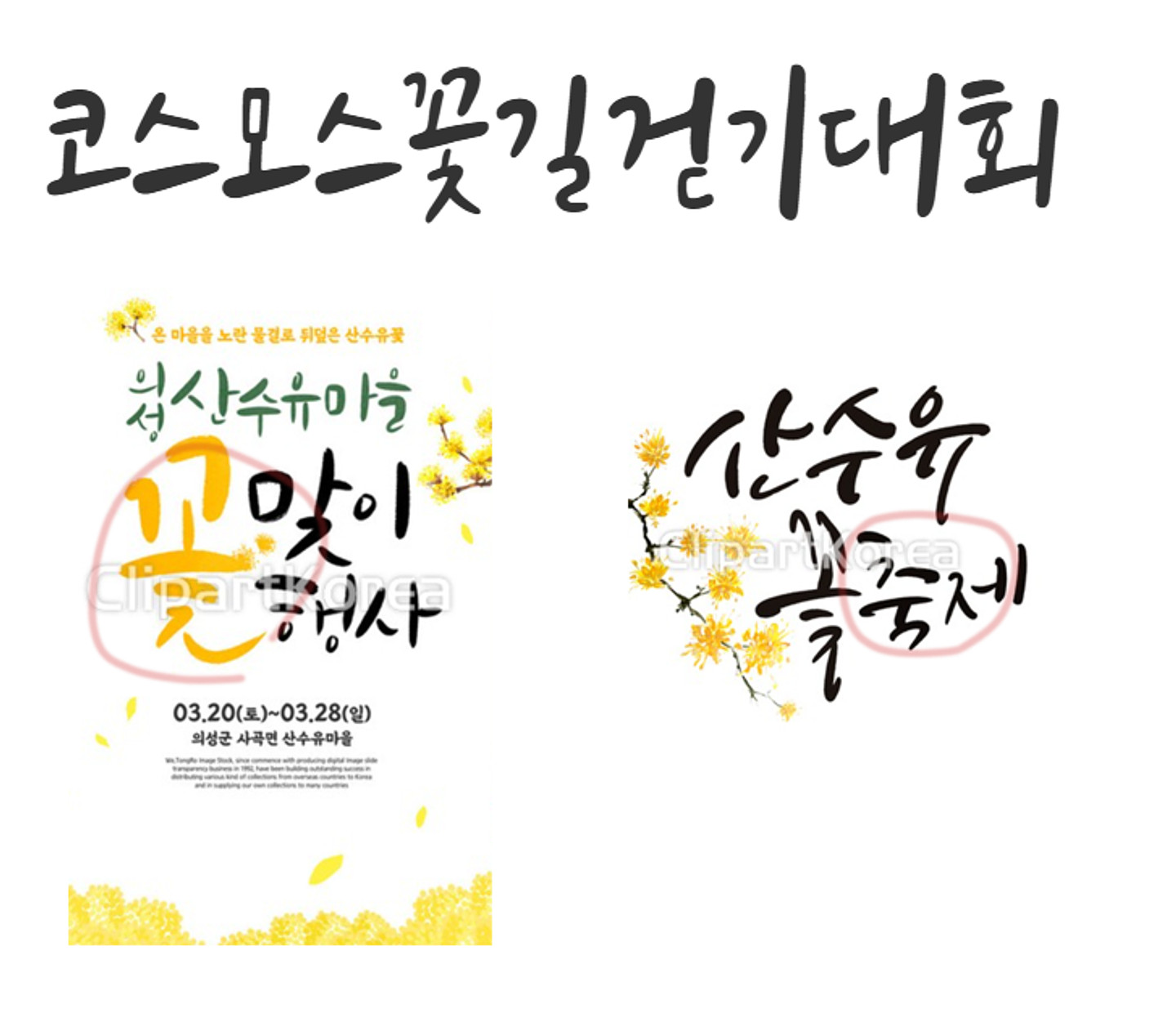
호법 꽃축제 (큰글씨) 코스모스꼴길 걷기대회 (오른쪽 위) 각각의 글씨체가 너무 궁금해요! 검색해도 찾기 쉽지 않네요 ㅠ
산돌공병각
(코스모스꽃길 걷기대회+호법) https://www.sandollcloud.com/font/20925/Yoon-Kongbyunggak-Soft 꽃축제는 캘리그라피로 직접쓴걸로 보입니다 https://www.clipartkorea.co.kr/search/preview?cont_code=ti302a17109&total=&menu=m&hdn=%EA%BD%83%EC%B6%95%EC%A0%9C&ska=2&sort=3&per=50&ad=off&page=1&nw=on&keyword=%EA%BD%83%EC%B6%95%EC%A0%9C%20%EC%BA%98%EB%A6%AC%EA%B7%B8%EB%9D%BC%ED%94%BC&vt=popup&popYn=Y https://www.clipartkorea.co.kr/search/preview?cont_code=ti360a1214&total=6814&idx=116&menu=m&img=https%3A%2F%2Fvrthumb.clipartkorea.co.kr%2F2018%2F03%2F22%2Fti360a1214.jpg&sm=5504723&hdn=%EA%BD%83%EC%B6%95%EC%A0%9C&ska=2&sort=3&per=50&ad=off&nw=on&keyword=%EC%B6%95%EC%A0%9C%20%EC%BA%98%EB%A6%AC%EA%B7%B8%EB%9D%BC%ED%94%BC&view=g&vt=popup&popYn=Y